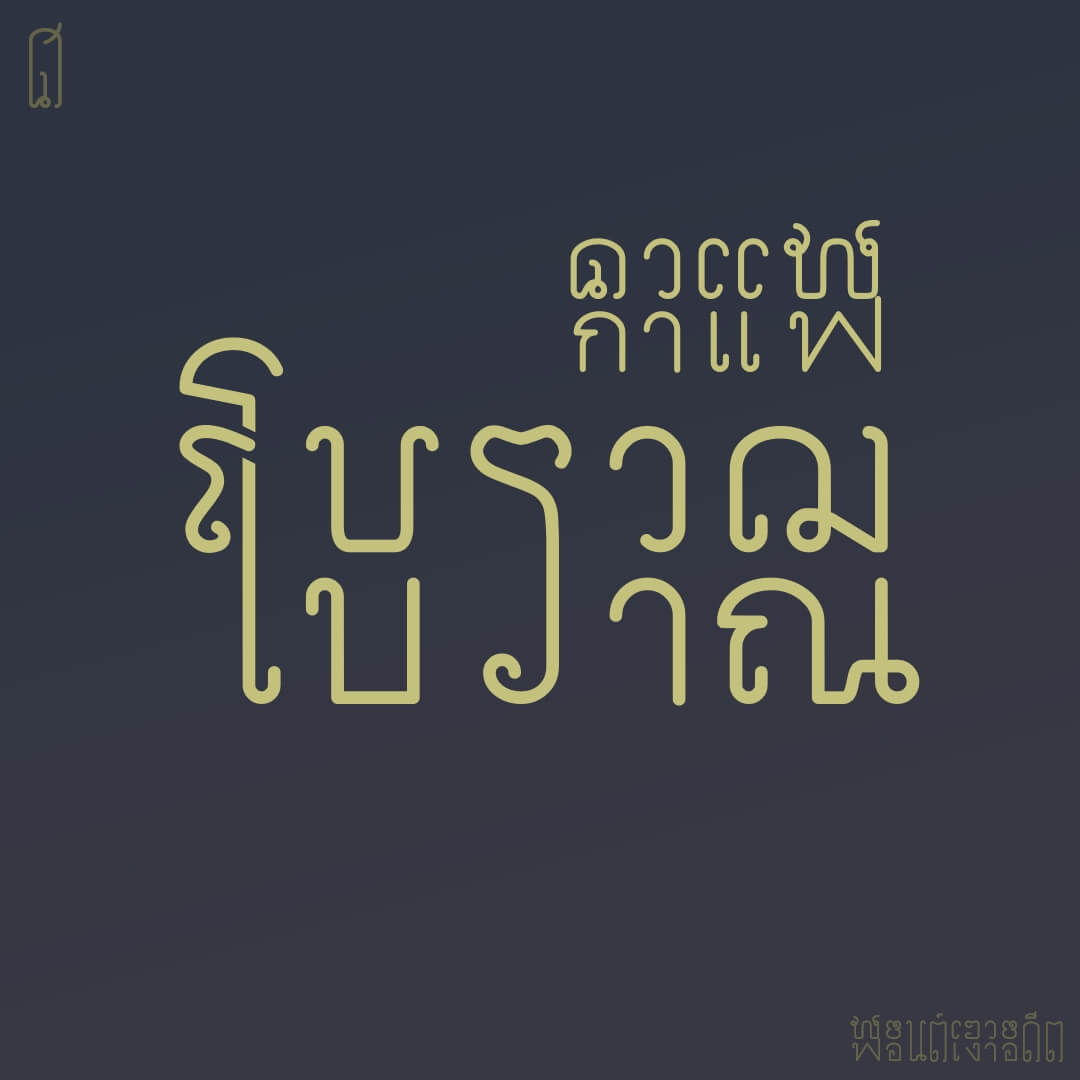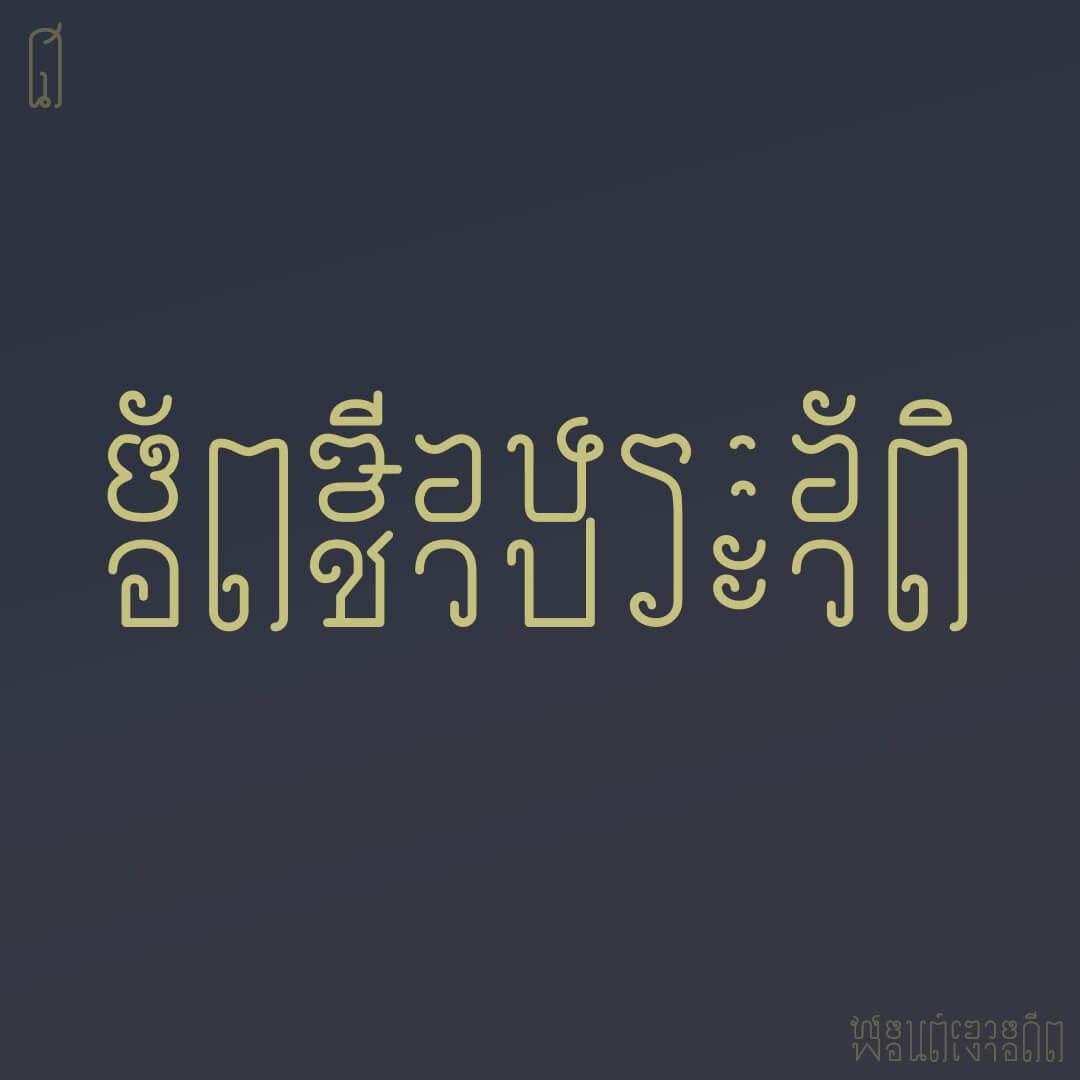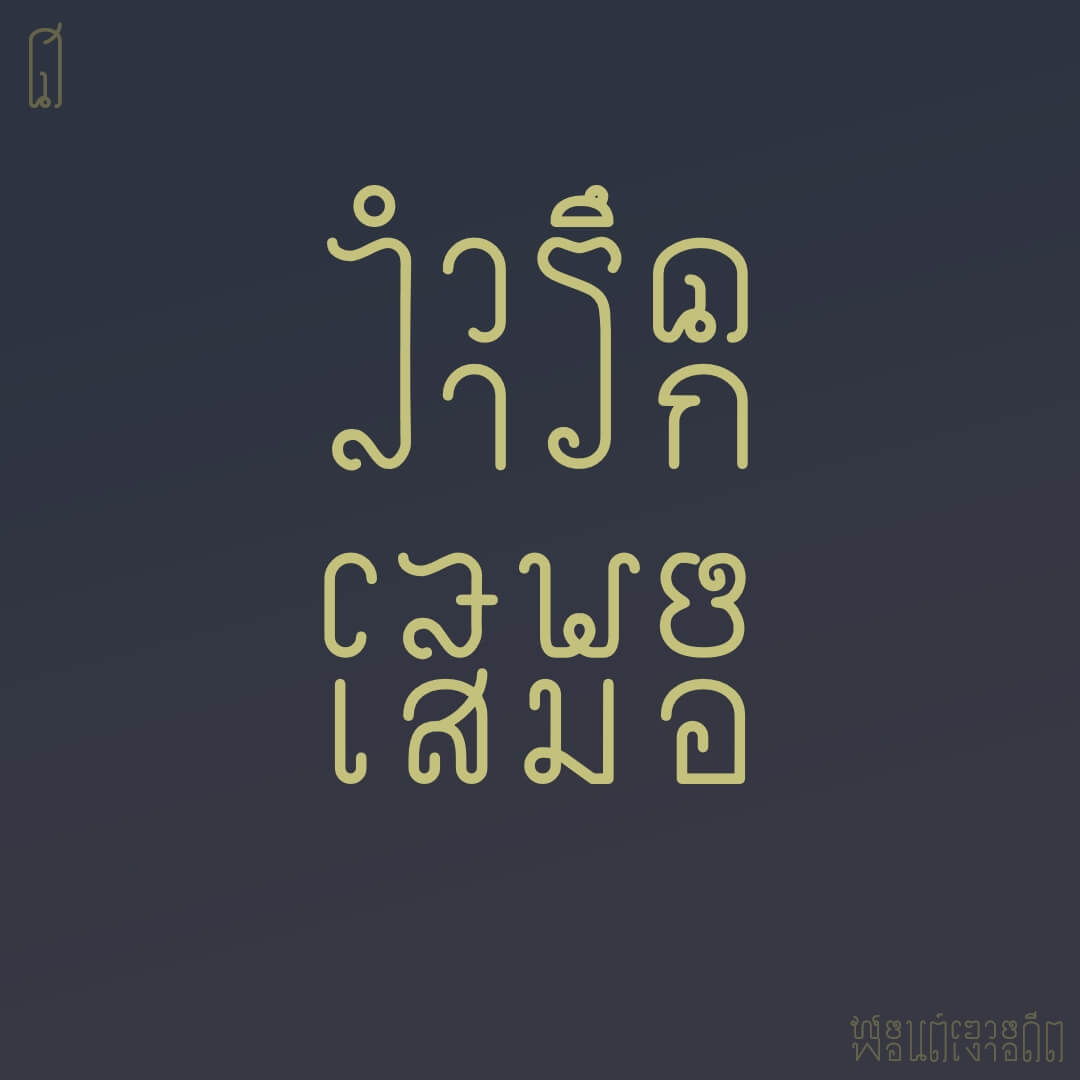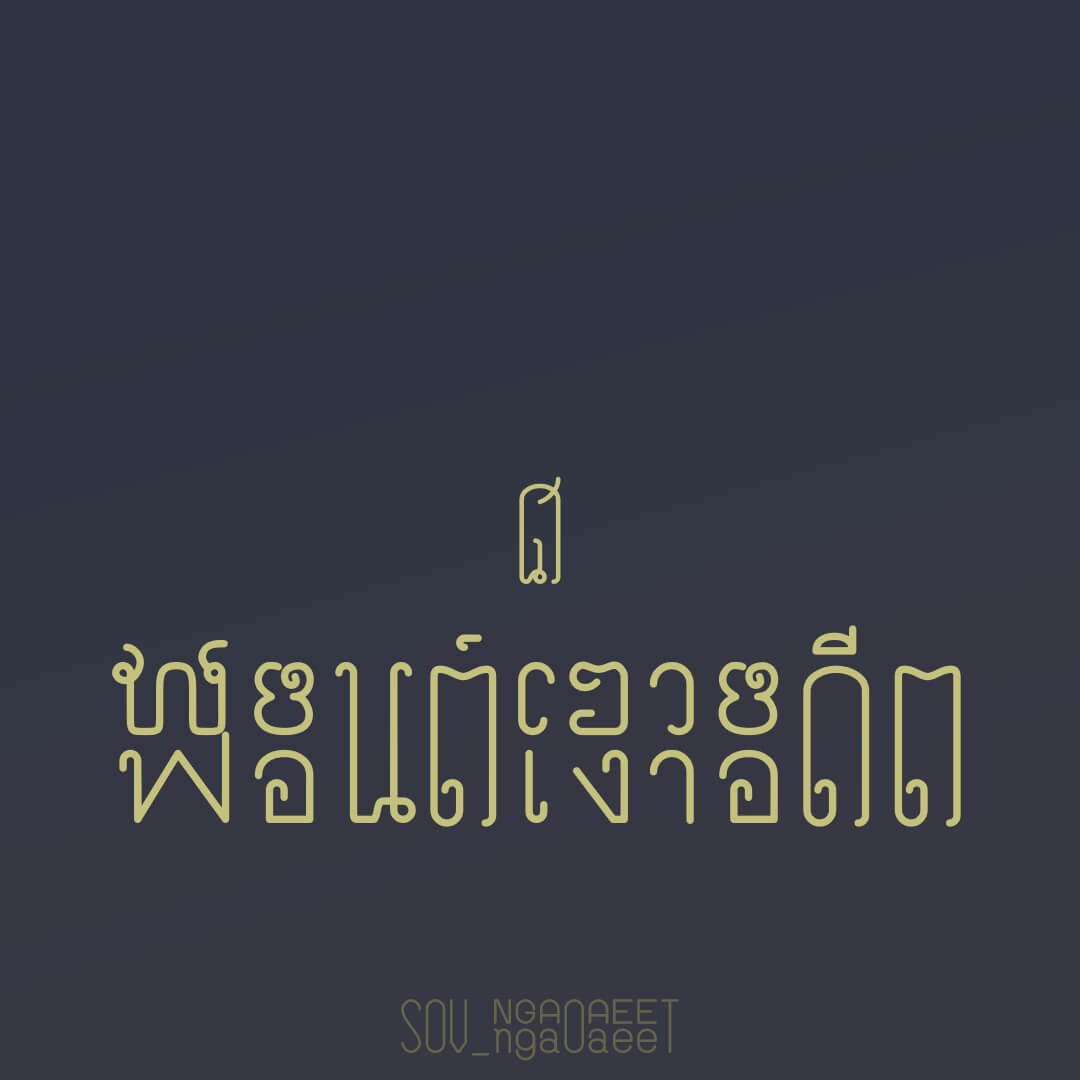
เงาอดีต (SOV_NgaoAdeet)
ฟอนต์เงาอดีต – งานทดลองฟอนต์ 2 ชั้น อักษรไทยตัวบนต้นแบบจาก จารึกหลักที่ ๑  ส่วนตัวล่างอักษรปัจจุบันแบบหัวเปิด เพื่อให้เห็นการเปลี่ยนรูปอักษรจากในอดีตมาปัจจุบัน ส่วนอักษรที่มีความคล้ายกันหรือไม่ทำให้สับสน จะทำการยึดอักษรเพื่อเป็นการแสดงให้เห็นความคงอยู่ หรือเปลี่ยนแปลงที่ค่อนข้างน้อย
หมายเหตุ ไม่ได้นำ สระ บนล่าง (ที่เขียนข้างหน้าพยัญชนะ) รูปวรรณยุกต์ และวิธีการเขียนอักษร (แบบอักษรติดกัน ห่างกัน) ของจารึกหลักที่ ๑ มาใช้นะครับ